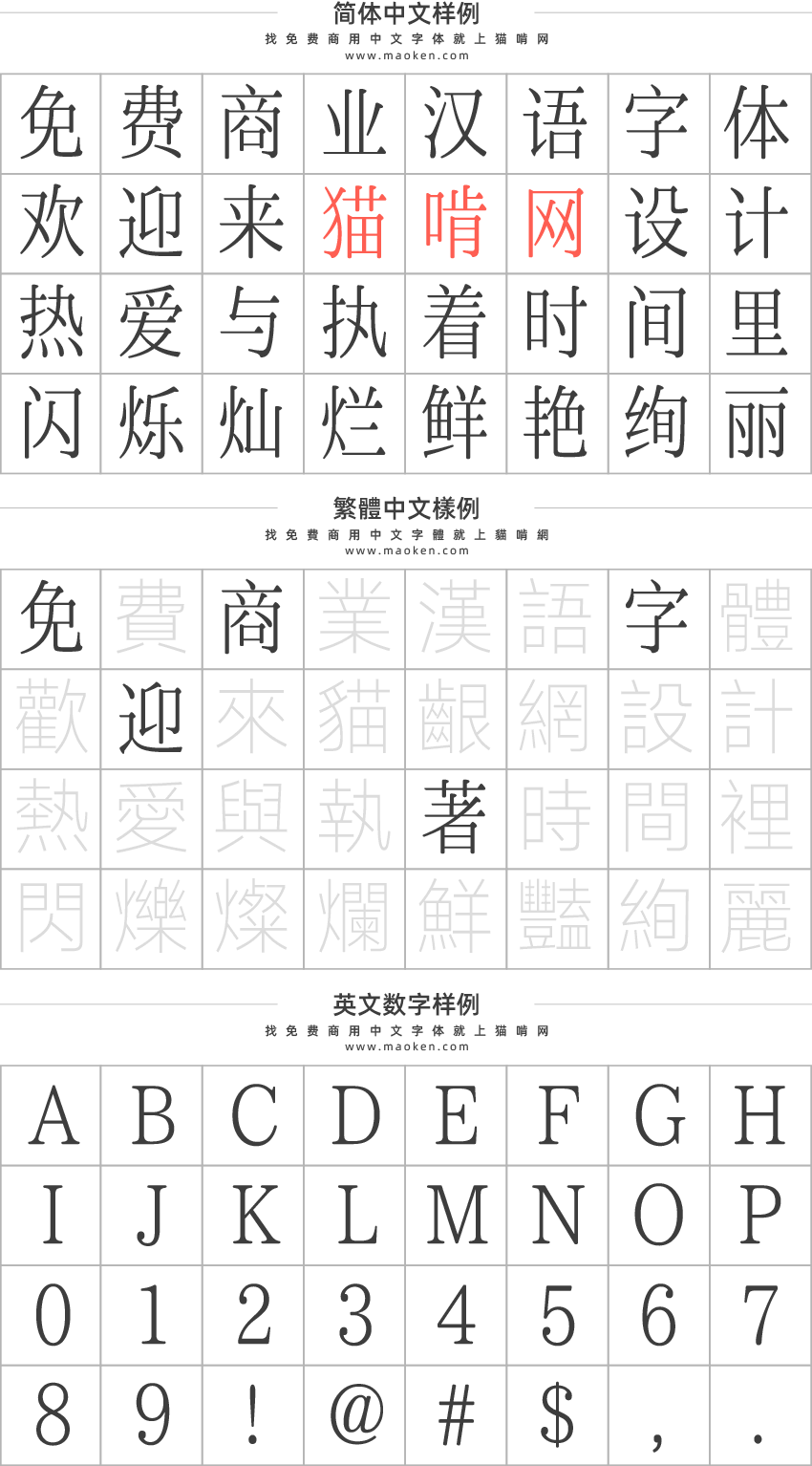
霞鹜铭心宋在こころ明朝体的基础上修改制作,将新致宋字面横向压缩 85%,并增加圆角,更加清瘦、圆润。(注:铭心宋所收字符相比于新致宋会有所欠缺,敬请留意。)
霞鹜铭心宋目前包含 GB/T 2312-1980 一级字、《通用规范汉字表》一级字、《现代汉语常用字表》3500 字。
非常喜欢这款字体,如果字间距能缩小一些就更好了
真好,完美去除了仿宋视觉歪斜感的, 同时保留了超强可读性和省墨的特性
期待完善, 真好看
这个看小说真行,就是字库太少了,等一等吧,我觉得这个字体真美
这个用来看小说挺爽啊
看着这个字体想到刻明朝字体了,刻明朝是正常大小的汉字和相对窄小的假名组合起来的,想用中文字体替换的话如果只是用新致宋替换的话就好像仍有优雅但丢失了纤细的特性,如果能用这铭心宋的话似乎就正好呢
霞鹜铭心宋:这个字形真的就很像 仿宋 的样式了。期待能持久维护、增补完善。赞!